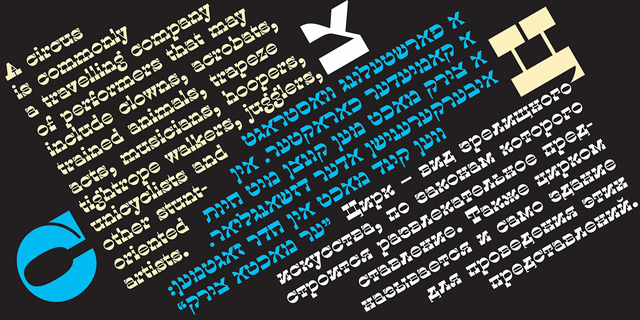
Caslon1821 – это возрожденный «итальянский» шрифт студии Caslon & Livermore, 1821 год. Этот шрифт быстро распространился по всей Европе и Америке. Он пришел в Российскую Империю из Франции и стал очень популярным в 30-х годах XIX века. Кириллические версии этого шрифта предлагали различные словолитни. В версии студии Apostrof есть поддержка иврита (с гласными). Шрифт разработали Виктор Харик и Константин Головченко в 2014 году.